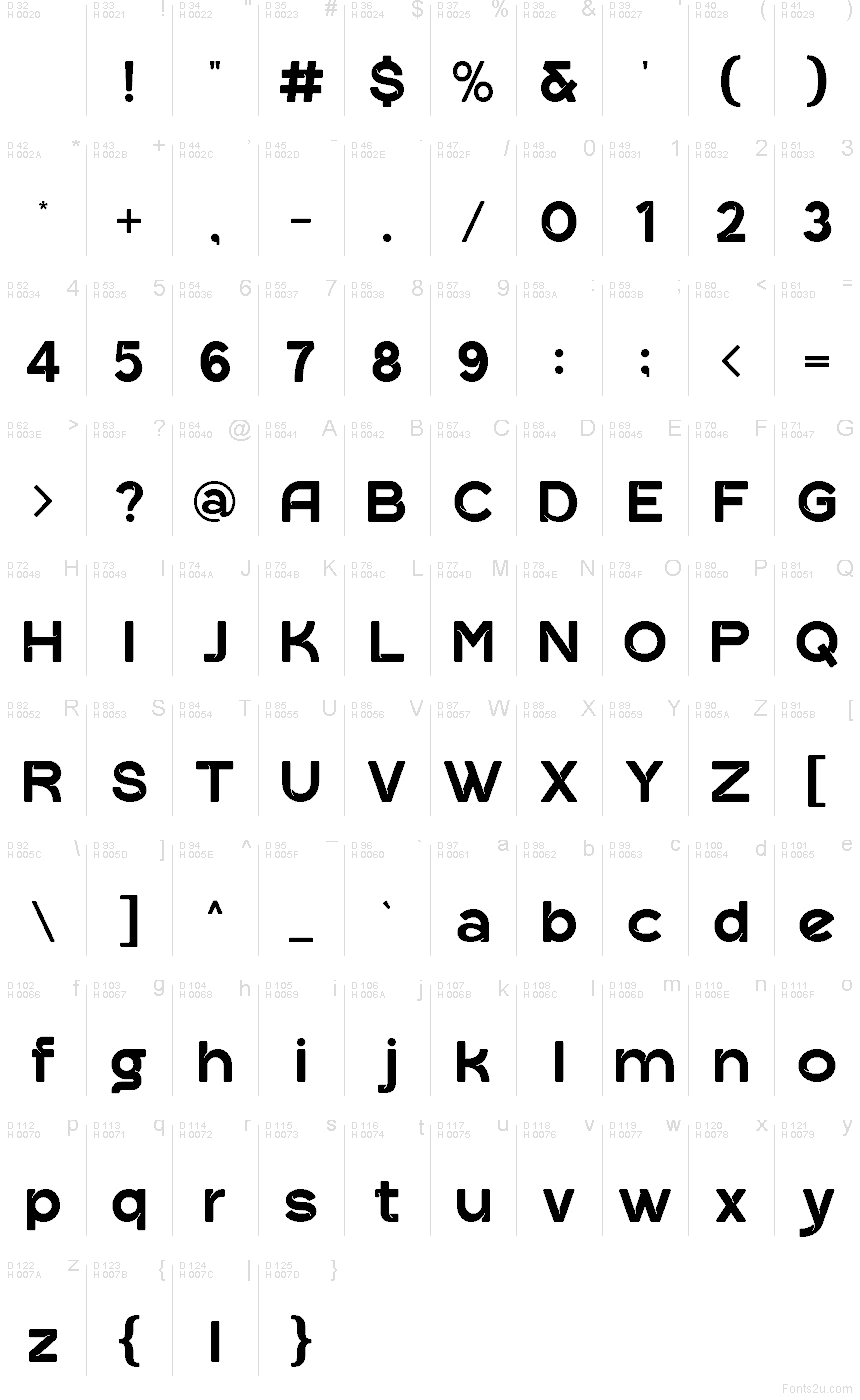
Poolary da Ermedia Studio é uma fonte display gratuita e de estilo groovy, construída a partir de traços grossos e arredondados e curvas geométricas marcadamente amplas. Pequenos cortes côncavos dão vida às formas suaves das letras.
Uma marca de moda independente e lúdica ou uma loja de discos poderia usar suas formas fluidas para branding, embalagens, pôsteres e produtos, especialmente quando um toque inspirado nos anos 1970 se adequa ao projeto. Suas alças exageradas também podem evocar discos de vinil, bolhas ou ilustrações circulares planas simples, permitindo que as letras se tornem parte da arte em vez de uma legenda neutra.